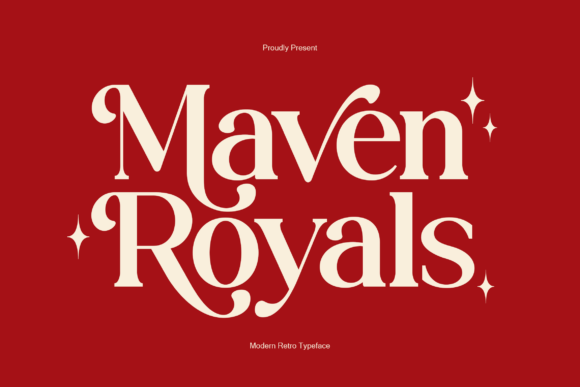
Maven Royals
適切なデザイン要素を見つけるのは難しい場合がありますが、Maven Royalsは作品を即座に引き立てる優れたコレクションを提供します。
POD(オンデマンド印刷)製品、結婚式の招待状、またはソーシャルメディアのグラフィックを作成している場合でも、Maven Royalsは理想的です。